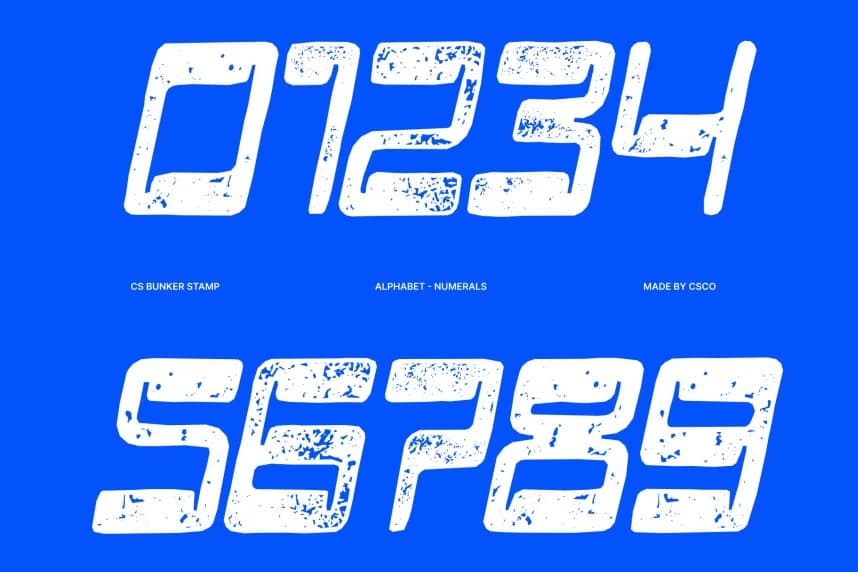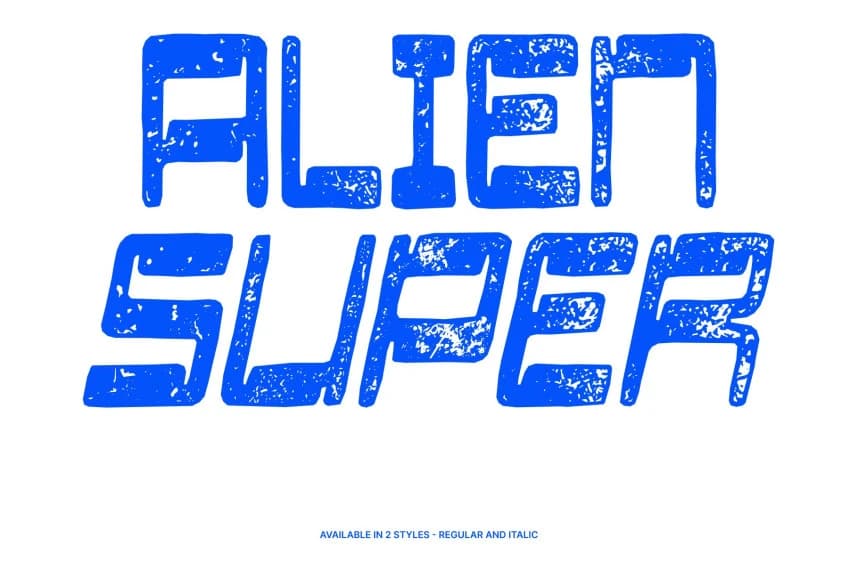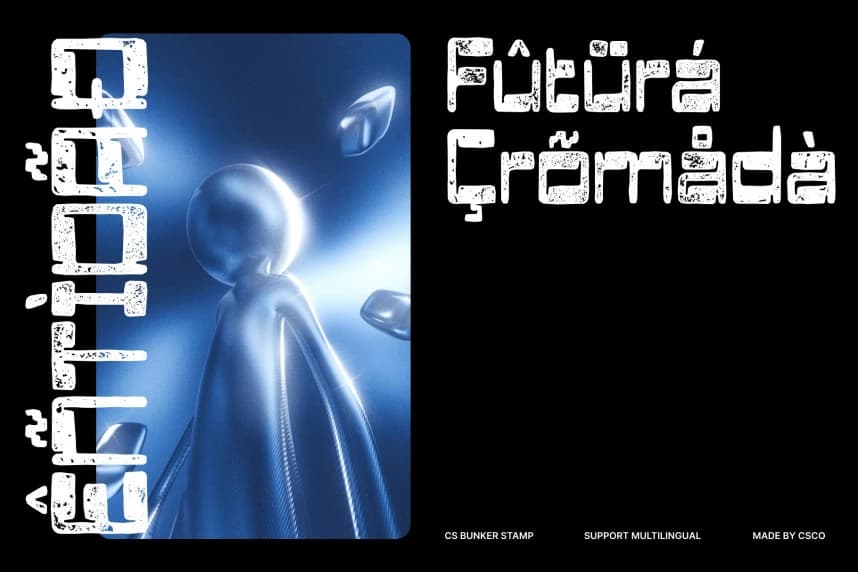
CS Bunker Stamp Yazı Tipi
CS Bunker Stamp Font – Ters Kontrast ile Dokulu Retro Neşesi, Belirgin Ters Kontrast Tasarımı. Bu, yatay vuruşların düşeylerden belirgin şekilde daha kalın olduğu çarpıcı bir ters kontrast stiline sahip bir gösterim yazı tipidir.
CS Bunker Stamp Font – Dokulu Retro Neşeyle Ters Kontrast ve Özgün Ters Kontrast Tasarımı. Bu, belirgin bir ters kontrast stiline sahip bir gösterim yazı tipidir; yatay çizgiler, dikey olanlardan belirgin şekilde daha kalındır.